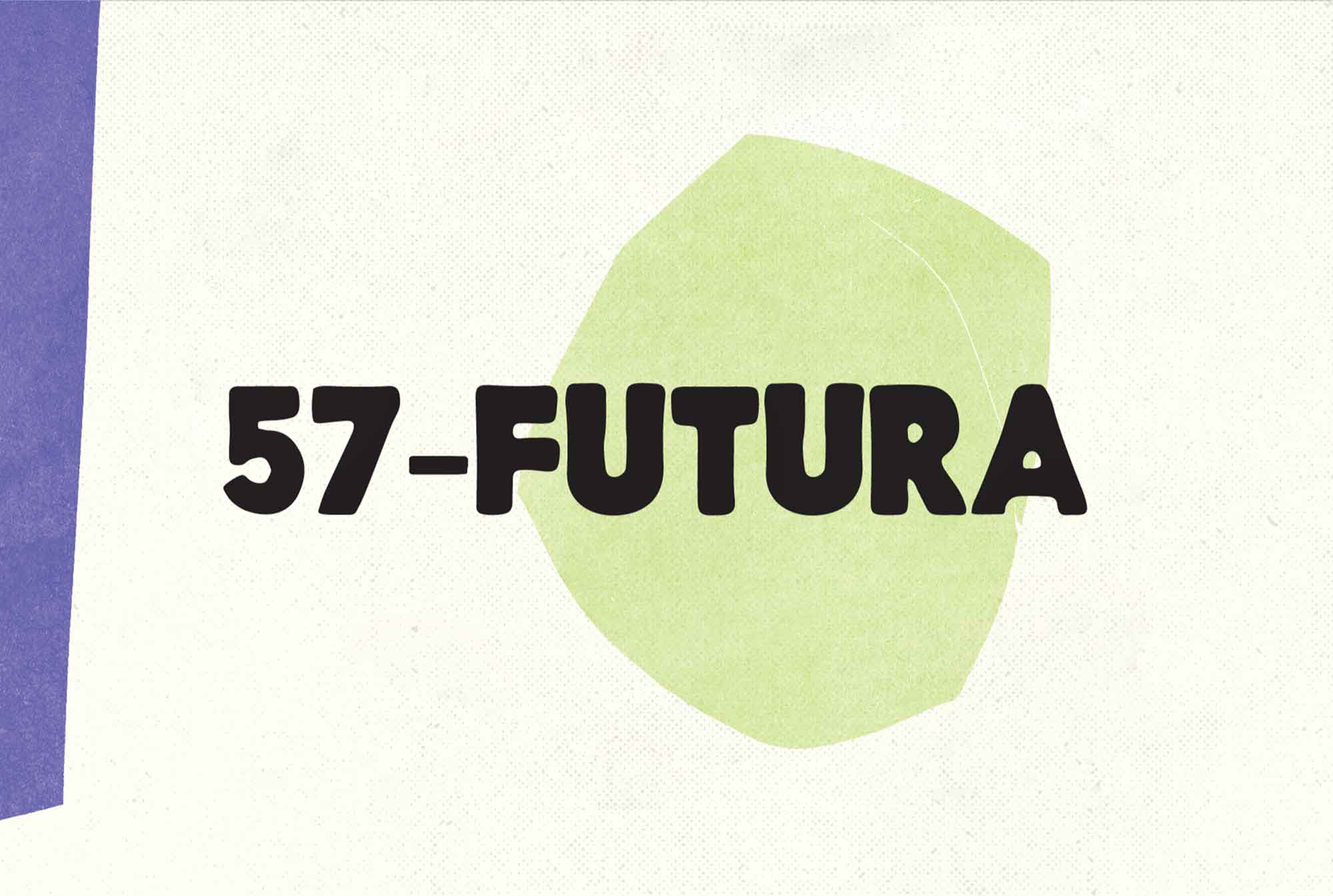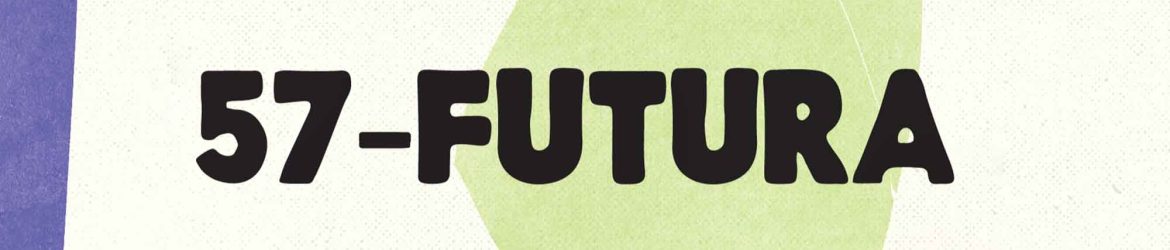
O mundo da gráfica tem um charme próprio que transmite um sentimento de nostalgia e elegância. Na categoria de fontes vintage, a 57 Futura Vintage apresenta uma combinação harmoniosa entre o antigo e o atual, oferecendo um visual que transmite a essência de um passado riquíssimo. Se você acredita que o antigo pode ser algo mais que simplesmente antiquado, então deve ter observado a influência dessa fonte vintage no design de marcas. É verdade, o Harley Davidson e o Dollar Shaving Club, duas das marcas mais respeitadas do mundo, incorporam essas fontes vintage em seus logos, criando um vínculo emocional com o público, transmitindo a ideia de uma história contagiante e respeito pelo longo tempo dedicado a suas marcas. A 57 Futura Vintage é mais do que apenas uma fonte: ela é um passo em direção à história, ao passado, e ao design que inspira.